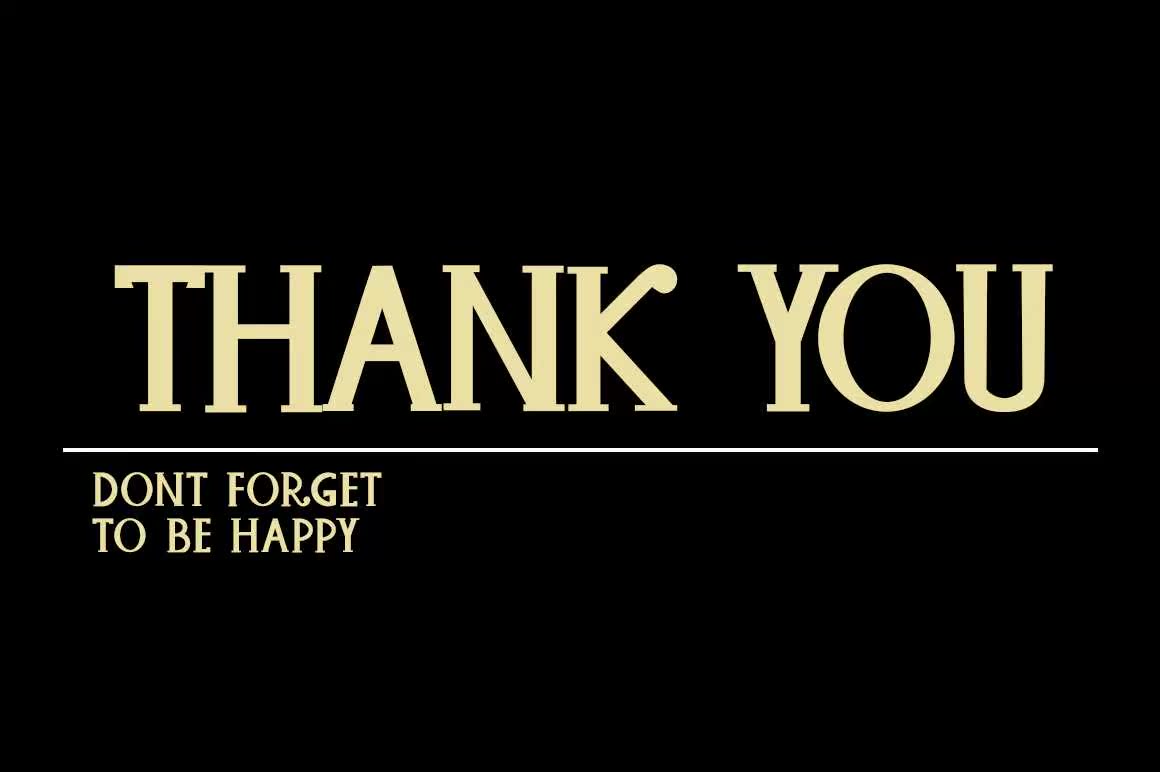
Baqueshand Amisavery Beautiful and Tractive Font.Font设计用于简化您的设计,如服装设计、服装、模型、标志设计、YouTube Banner和许多其他工艺品。使用此字体,您的业务将在市场上看起来更美丽、更持久。与此不同,此字体简单易懂。Baqueshandtamisavery Beautiful and Tractive Font。Font设计为简化您的设计,如服装设计、服装、模型、标志设计、YouTube Banner和其他许多工艺品。使用此字体,您的业务将在市场上看起来更加美丽和坚挺。与此不同的是,这一点非常简单和容易。